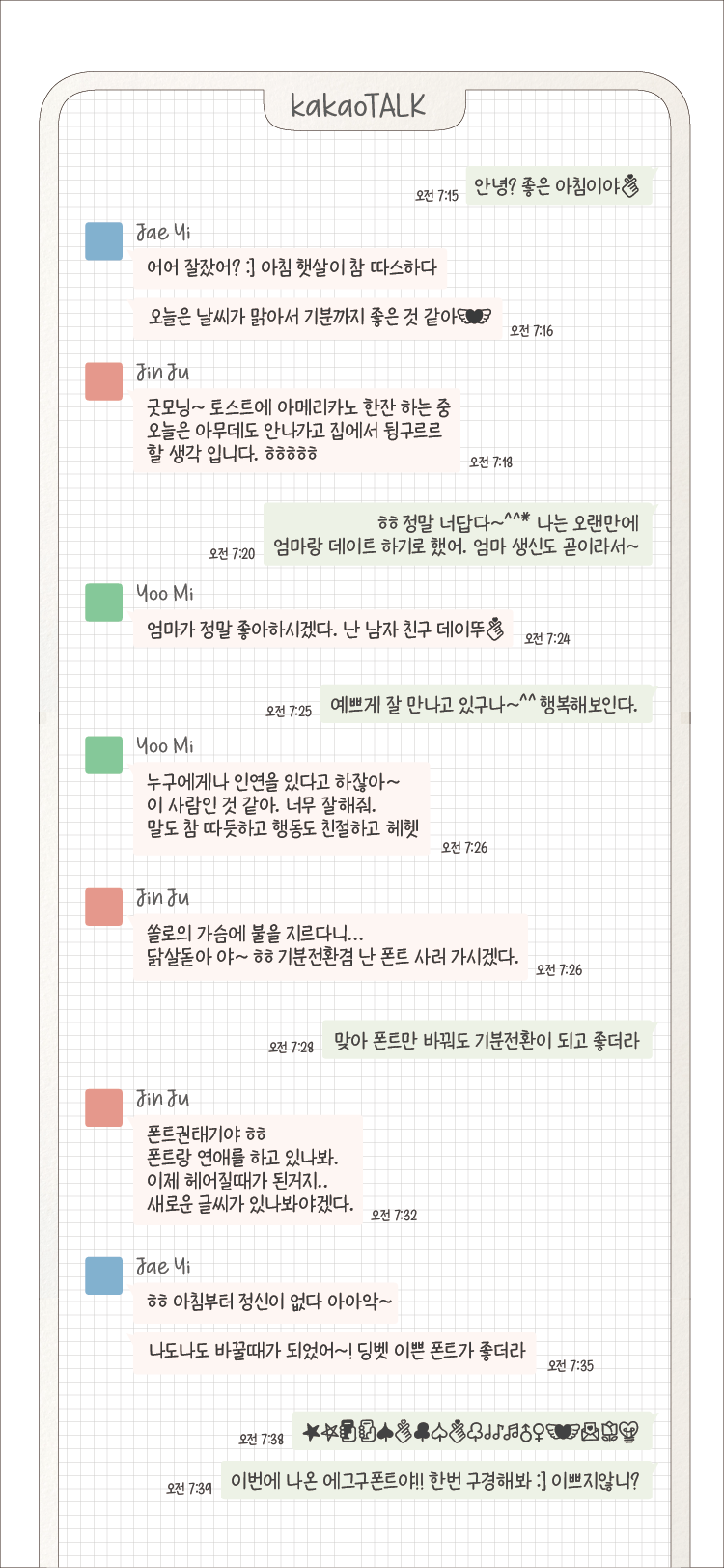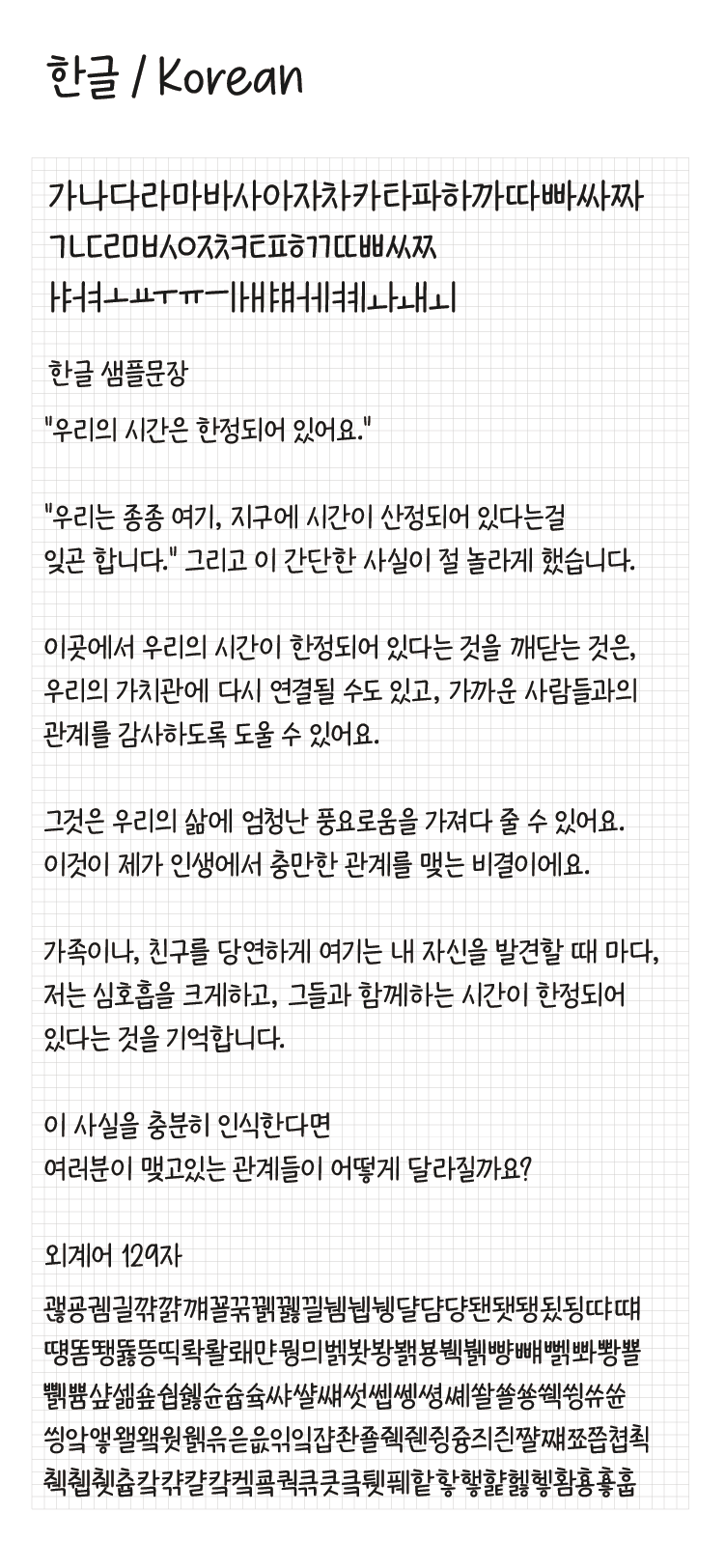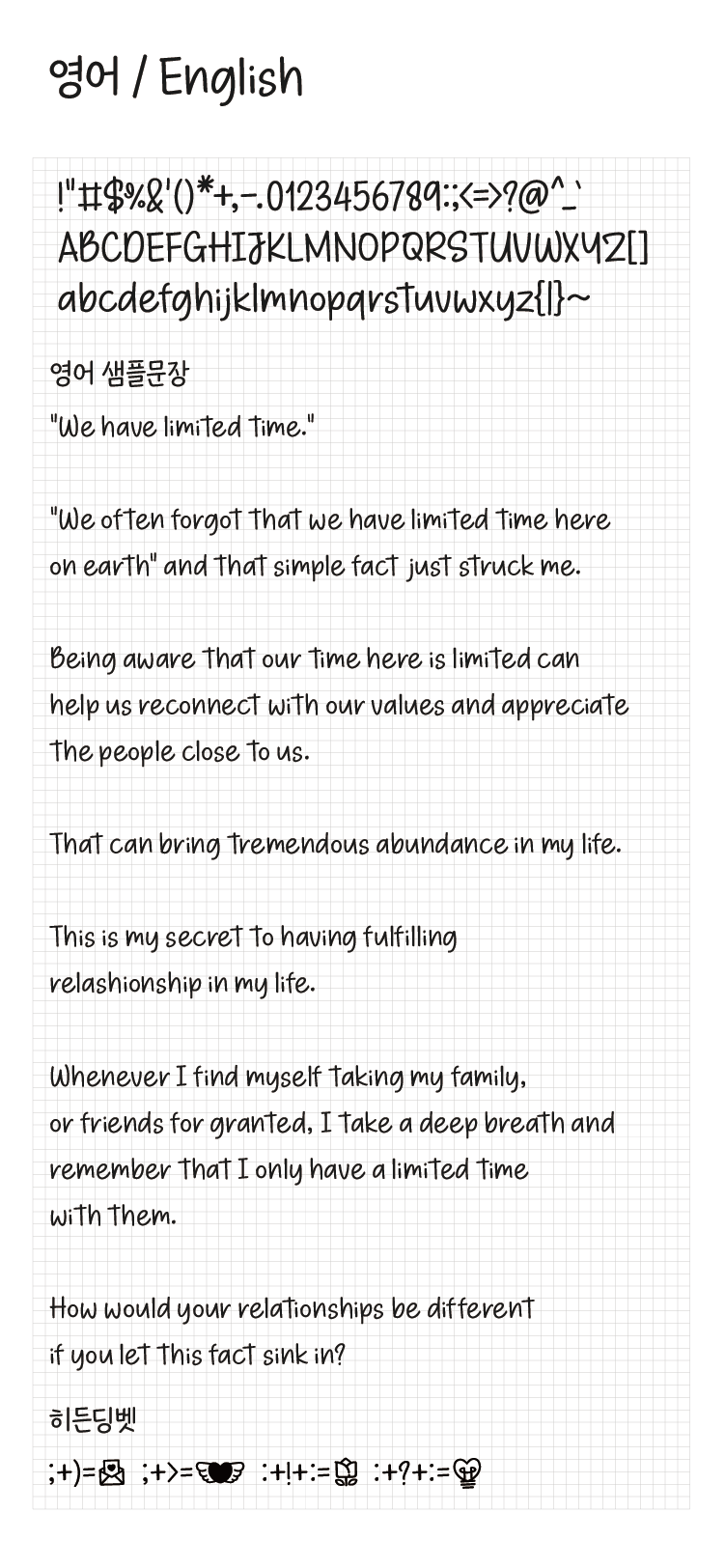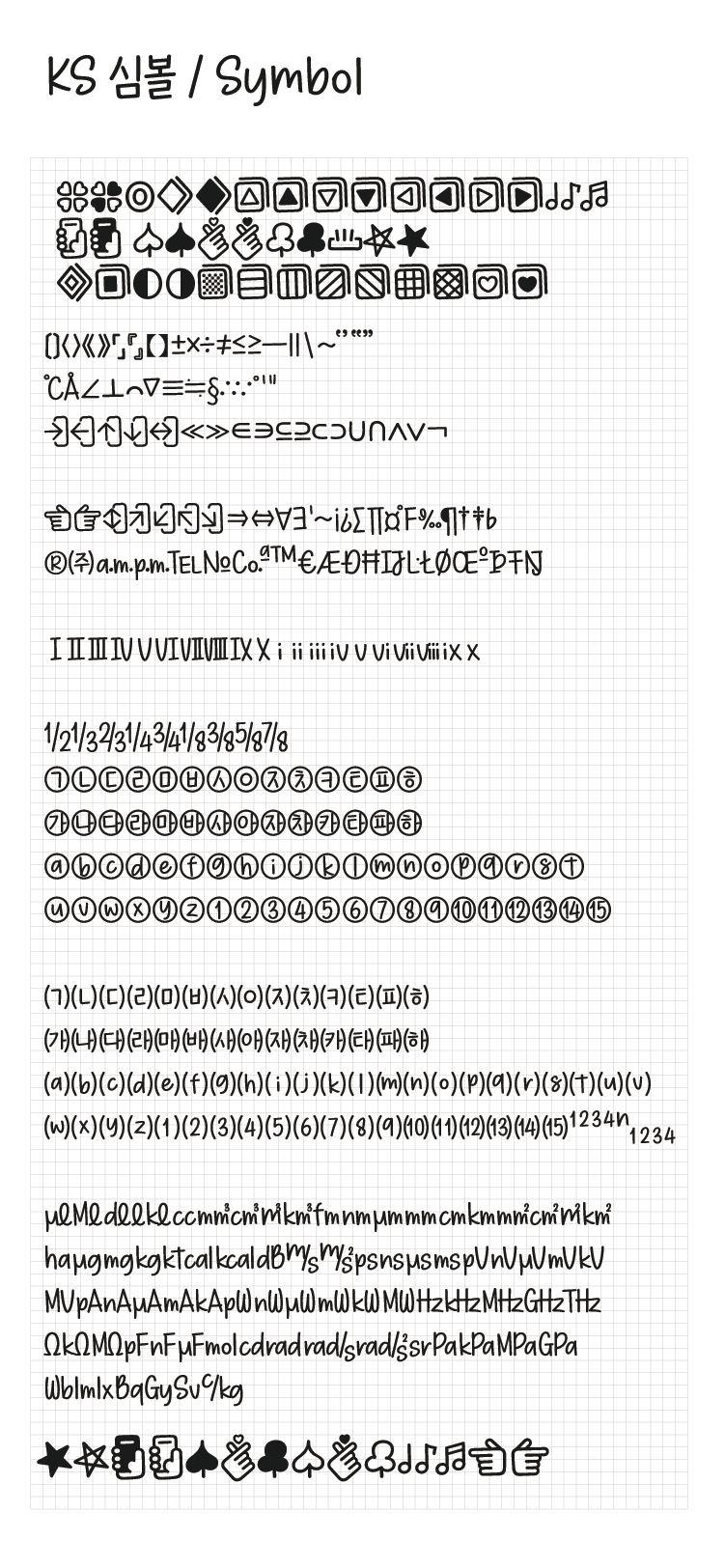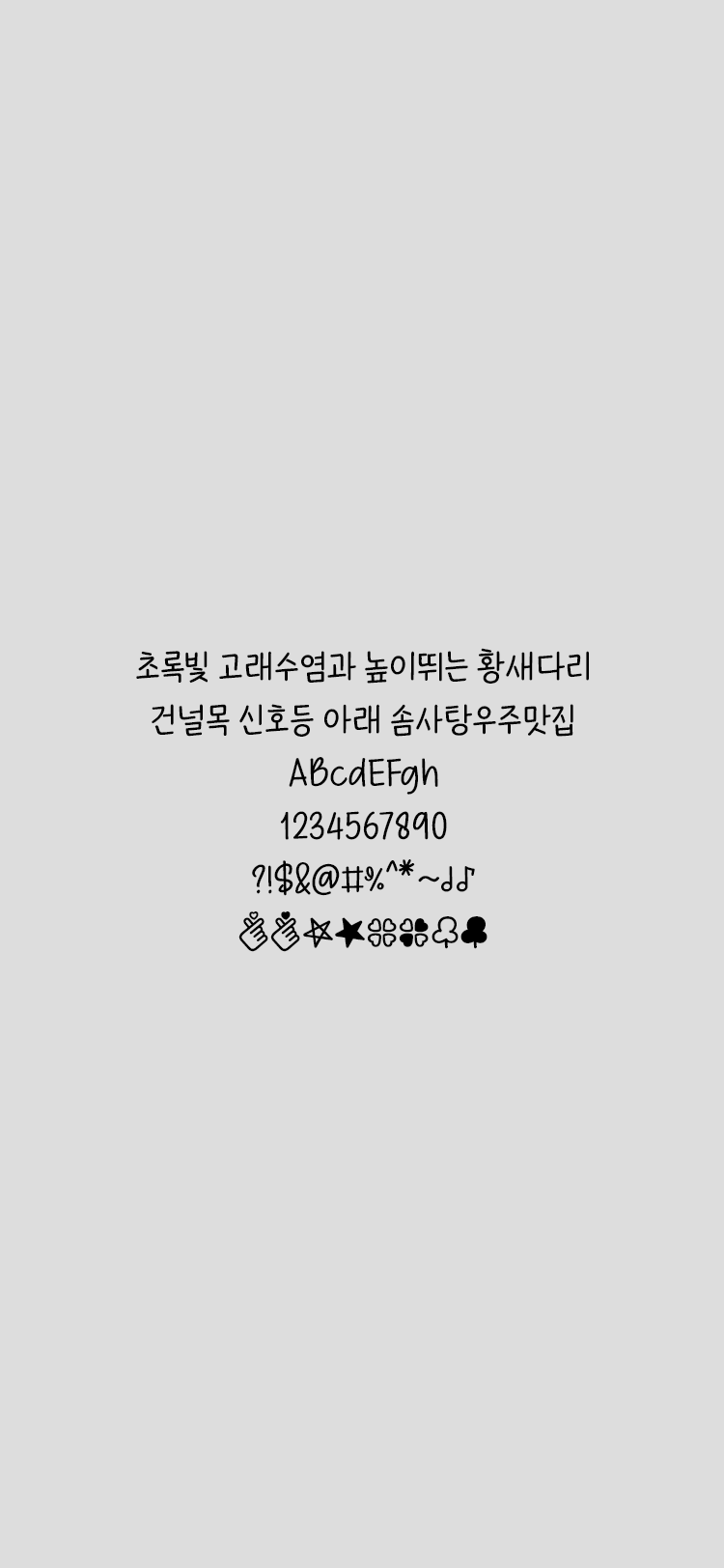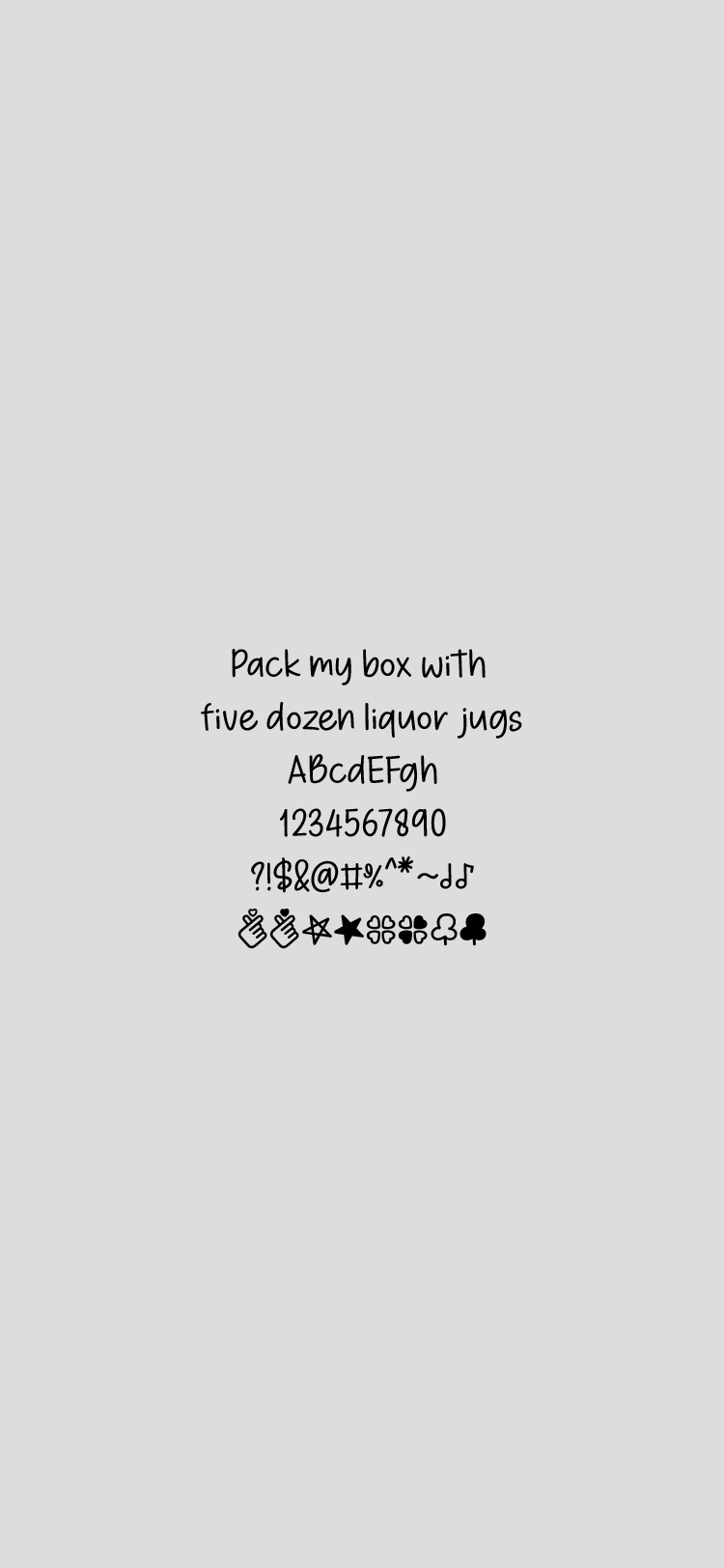
Egg9 단정한글씨체
Egg9font
모던하고 깔끔한 스타일입니다. 히든딩벳의 경우 ;> ;) :!: :?: 입력하시면 나옵니다.
• 한선주
• 한글 11,172자 / 라틴 95자 / 부호 985자 / 추가 글리프 4자
• Egg9 단정한글씨체 / Egg9 NeatFont